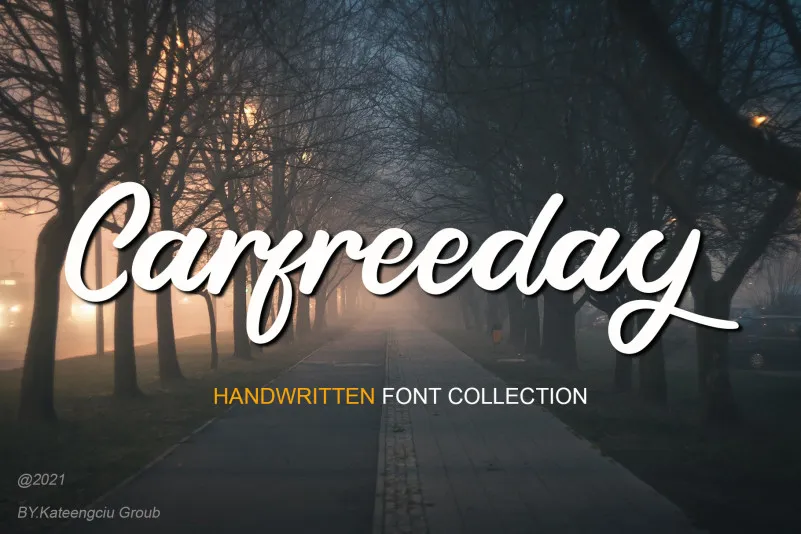
A fonte ‘Carfreeday Font’ é uma seleção ideal para quem busca estilos únicos e carregados de personalidade. Criada pelo designer kateengciu, essa fonte hand-writtene tem um toque delicado e dinâmico que irá enriquecer seus projetos em texturas variadas e sofisticadas. Seus traços quirkys e divertidos ajudarão a transformar ideias simples em obras de arte realistas e encantadoras. Esta font é perfeita para aqueles que valorizam um toque peculiar, seja em design gráfico, ilustrações ou até mesmo em textos legais. Experimente ‘Carfreeday Font’ e descubra seu potencial único para criar expressões únicas e vibrantes.